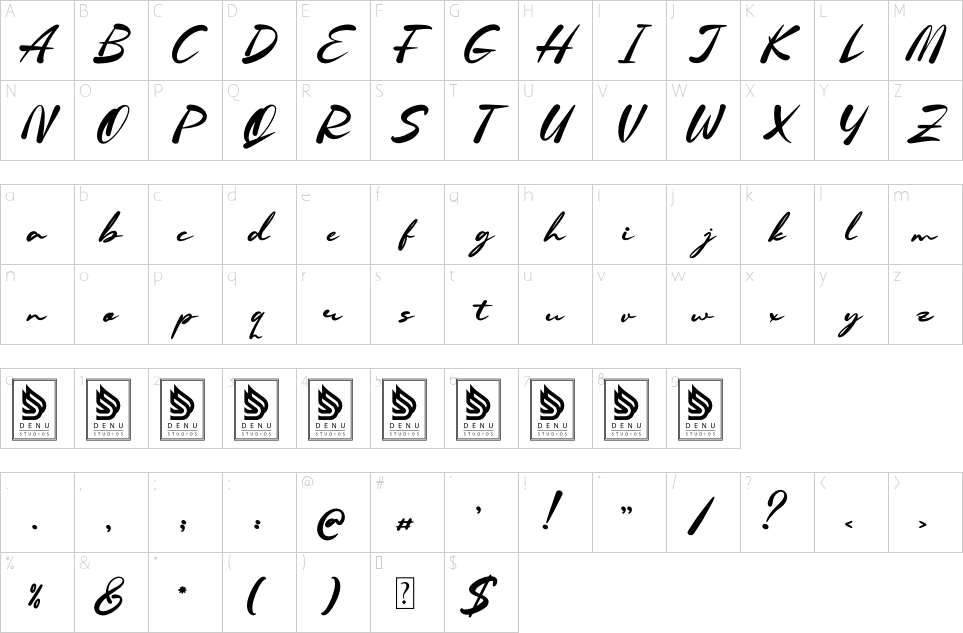
Descubra a tranquilidade das letras com a Dwimsy Mellowdi, uma fonte disponível gratuitamente para Windows e Mac. Desenhada pelo designer Gracetypestudio, esta fonte é perfeita para quem busca um estilo suave e acolhedor em projetos de escrita ou design gráfico. Com sua elegância natural, a Dwimsy Mellowdi traz tranquilidade aos seus projetos, tornando-os ainda mais atraentes e profissionais. Seja para criar cartazes com um toque de simplicidade ou escrever textos informativos em documentos de trabalho, esta fonte garante uma experiência gráfica confortável e relaxante. Descubra por si mesmo o charme da Dwimsy Mellowdi hoje!